Tổng hợp font bảng chữ cái thư pháp: Vẻ đẹp cổ điển, nghệ thuật trong từng nét chữ
Thư pháp từ lâu đã là một nét đẹp văn hóa truyền thống, thể hiện sự tinh tế, sáng tạo và dấu ấn riêng của người viết. Đặc biệt là ngày nay, với sự phát triển của công nghệ, nghệ thuật này không chỉ được thể hiện qua bút lông và mực tàu mà còn qua những bộ font bảng chữ cái thư pháp độc đáo. Trong bài viết này, FPT Shop sẽ tổng hợp những font chữ thư pháp đẹp, giúp bạn dễ dàng sử dụng để viết câu đối, thiết kế ảnh nghệ thuật hay tạo điểm nhấn cho văn bản.
Font bảng chữ cái thư pháp là gì?
Font bảng chữ cái thư pháp là kiểu chữ được lấy cảm hứng từ nghệ thuật viết chữ bằng bút lông truyền thống. Điểm nổi bật của font chữ này là những đường nét mềm mại, uyển chuyển và phóng khoáng đặc trưng của thư pháp. Với vẻ đẹp tinh tế và đậm chất nghệ thuật, font chữ thư pháp được ứng dụng trong nhiều thiết kế để mang đến sự sang trọng và giá trị văn hóa cho mỗi tác phẩm.
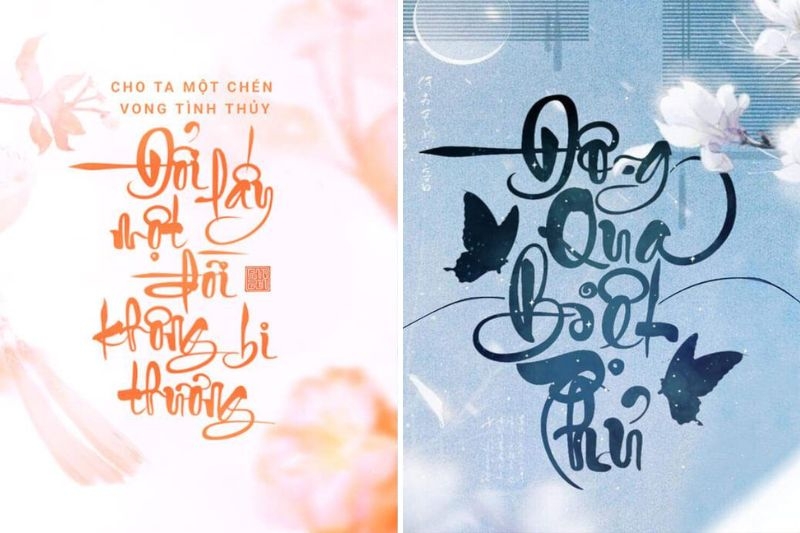
Top 10 font bảng chữ cái thư pháp đẹp, ấn tượng nhất
Dưới đây là top 10 font bảng chữ cái thư pháp đẹp và độc đáo nhất mà bạn có thể sử dụng trong các thiết kế của mình. Mỗi font chữ đều mang một phong cách riêng và phù hợp với nhiều loại ấn phẩm khác nhau. Hãy cùng FPT Shop khám phá và lựa chọn cho mình một kiểu chữ phù hợp nhé!
Font VN Lovelista
VN Lovelista được biết đến với các đường nét thư pháp mềm mại, uyển chuyển nhưng vẫn giữ được sự tinh tế và chắc chắn. Đặc biệt là sự kết hợp hoàn hảo giữa nét thanh và nét đậm không chỉ mang lại chiều sâu mà còn tôn lên tính nghệ thuật cho văn bản. Không khó hiểu khi Lovelista được giới sáng tạo ưu ái khi ứng dụng vào những thiết kế mang đậm bản sắc văn hóa Việt.
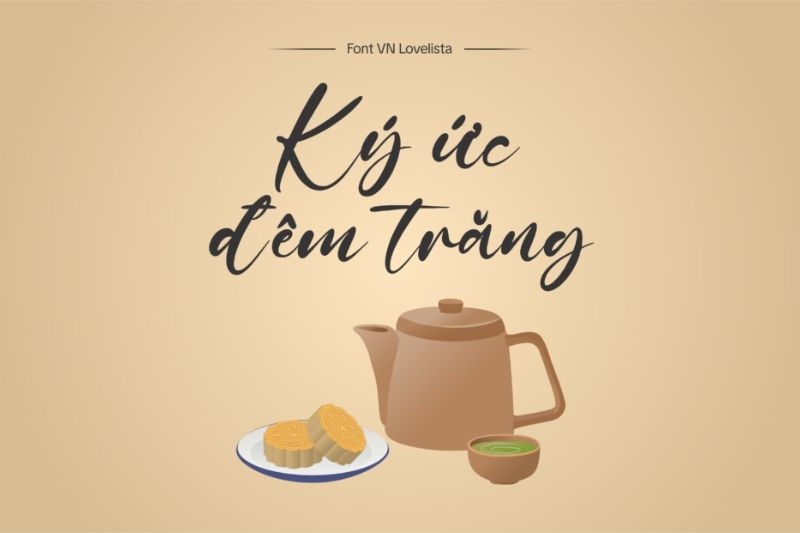
Font VN Opulent Brush
Font Opulent Brush là sự kết hợp táo bạo giữa nét mạnh mẽ, dứt khoát và phong thái phóng khoáng, tự do. Vì mô phỏng cách viết thư pháp của các ông đồ xưa, kiểu chữ này mang đến cảm giác cổ điển nhưng vẫn toát lên vẻ uy nghi, thần thái. Chính vì vậy, Opulent Brush thường được dùng cho các thiết kế mang tính nghi lễ, trang trọng như câu đối Tết hay ấn phẩm văn hóa dân gian.
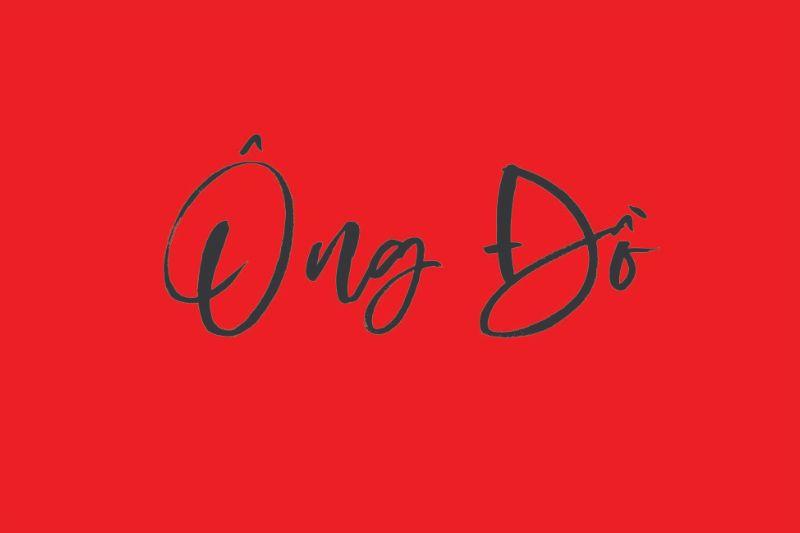
Font chữ Bendigo
Font bảng chữ cái thư pháp Bendigo nổi bật với sự tỉ mỉ và trau chuốt trong từng đường nét, đặc biệt là kiểu chữ hoa. Với vẻ đẹp hài hòa, Bendigo là lựa chọn hoàn hảo cho việc thiết kế tên thương hiệu, logo hoặc các ấn phẩm đòi hỏi tính trang trọng cao như giấy khen, thiệp mời, chứng chỉ,...
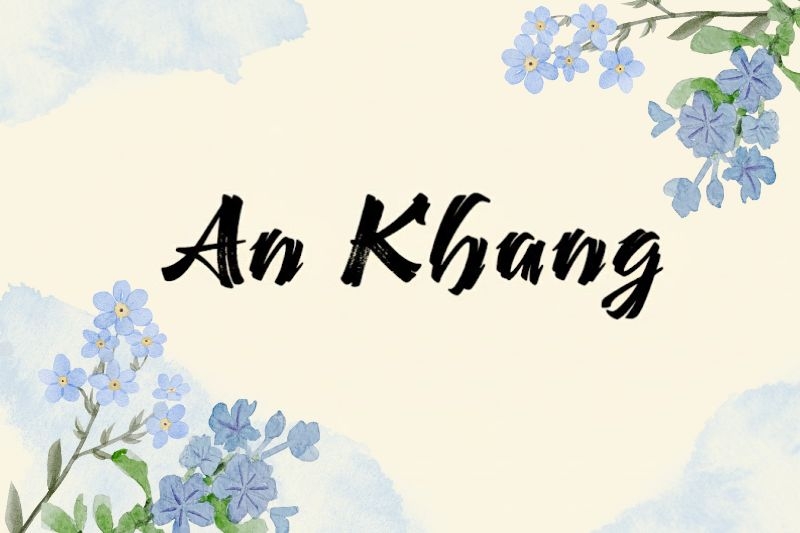
Font LNTH Watermark
Font LNTH Watermark được nhiều người yêu thích bởi những đường nét thanh mảnh, uốn lượn nhưng vô cùng thanh lịch. Kiểu chữ này gợi lên cảm giác nhẹ nhàng, yên bình như dòng nước chảy, cực kỳ lý tưởng cho các thiết kế thiên hướng tâm linh và thiền định. Vì lẽ đó mà bạn dễ dàng bắt gặp font chữ này trong các quyển Phật giáo, bảng hiệu cửa hàng phong thủy hay bìa kinh kệ.
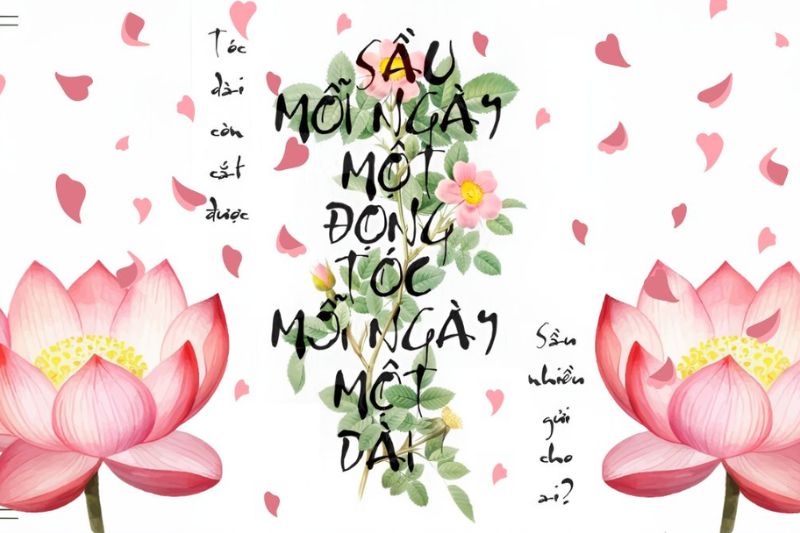
Font LNTH Dieter Steffmann
Font LNTH Dieter Steffmann là sự hòa quyện giữa nét thanh thoát, uyển chuyển và phong cách tươi mới nhưng vẫn giữ được vẻ trang trọng đặc trưng của thư pháp. Với tính thẩm mỹ cao, kiểu chữ này thường được dùng trong các thiết kế mang tính cảm xúc như thiệp chúc mừng, tri ân và ấn phẩm cho sự kiện lễ hội.
Bên cạnh đó, LNTH Dieter Steffmann cũng phù hợp để làm tài liệu giảng dạy, bìa sách hay quà tặng thủ công mang dấu ấn cá nhân.
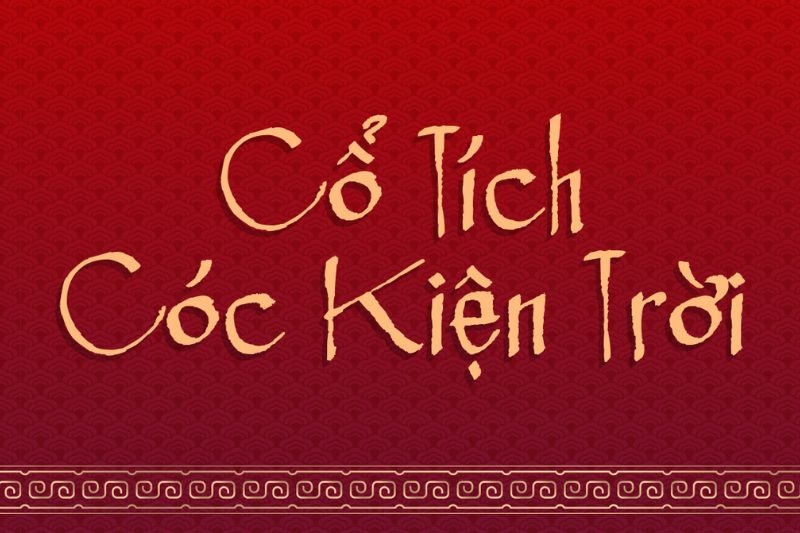
Font chữ Thành Công
Font bảng chữ cái thư pháp Thành Công gây ấn tượng bởi sự phá cách độc đáo nhưng vẫn giữ được nét văn hóa truyền thống. Những nét chữ dày, sắc sảo của font mang lại cho thiết kế cảm giác chắc chắn, mạnh mẽ và đầy cá tính. Ngày nay, font Thành Công thường được ứng dụng trong các ấn phẩm mang đậm không khí xuân như thiệp chúc Tết, bao lì xì hay quà handmade.
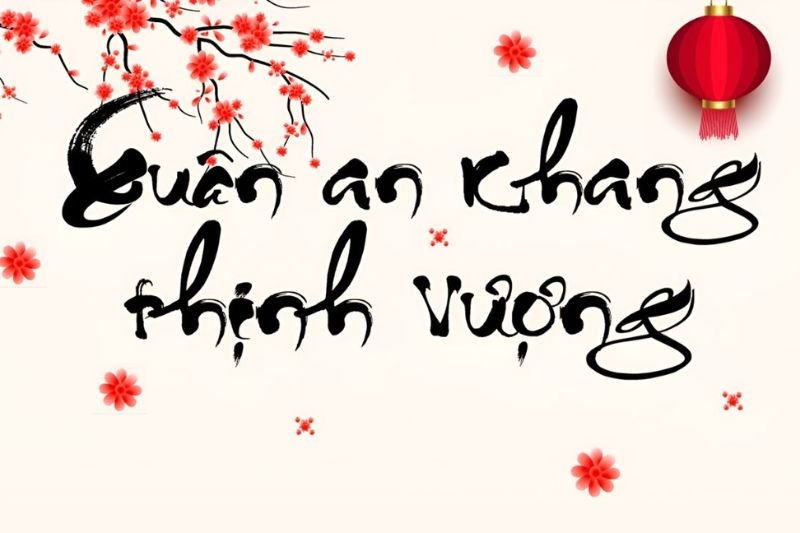
Font SVN Hottroof Semhesta
Font SVN Hottroof Semhesta sở hữu những đường nét mềm mại, uyển chuyển nhưng vô cùng tinh tế. Đặc biệt là kiểu chữ này còn mang đến một luồng năng lượng thanh tịnh và thiền định cho người xem. Có lẽ vì vậy mà Hottroof Semhesta được ưu tiên sử dụng cho các tác phẩm mang tính tĩnh tâm như kinh Phật, tranh thư pháp và các tài liệu hướng dẫn thiền.
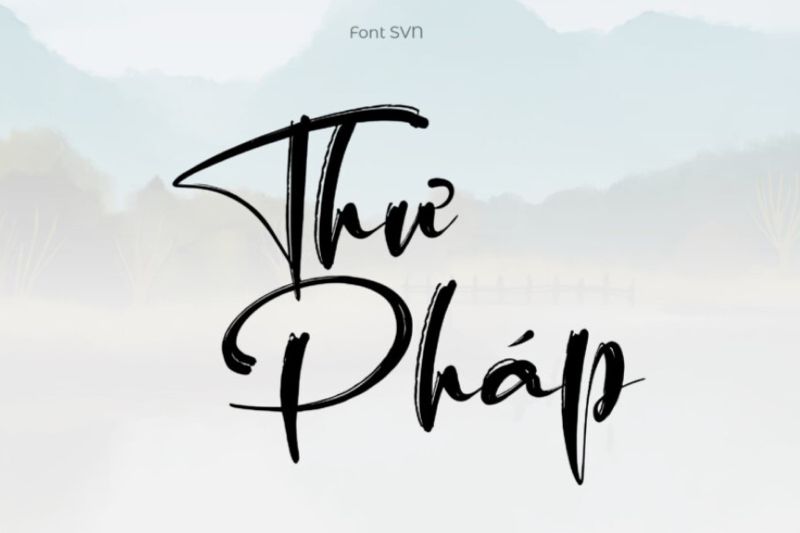
Font chữ Công Thuỷ
Font Công Thuỷ tái hiện trọn vẹn phong cách viết chữ của người xưa, nổi bật với những đường nét dày dặn, mạnh mẽ và các nét gạch đậm dứt khoát. Với nét đẹp văn hóa cổ điển, font bảng chữ cái thư pháp này phù hợp để thiết kế câu đối, thư pháp số hoặc các sản phẩm mang đậm dấu ấn truyền thống.
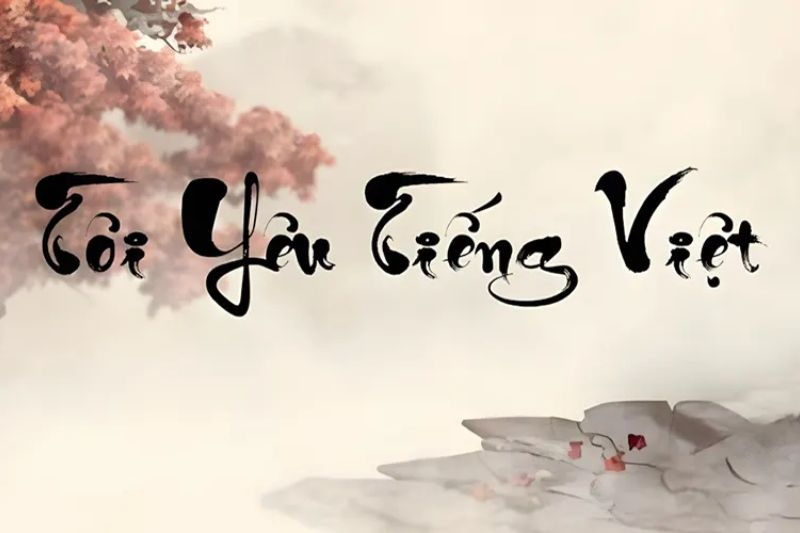
Font thư pháp Tiểu Tự
Font Tiểu Tự được tạo nên từ sự giao thoa giữa nét bút mềm mại và các điểm nhấn nhá đậm nhạt tinh tế. Từng đường nét đều được uốn lượn tinh xảo, thể hiện sự uyển chuyển, thanh thoát nhưng không hề thiếu đi sự dứt khoát. Do đó, font này rất phù hợp cho thiết kế mang tính nghệ thuật cao như poster, bìa sách, thiệp mời và các vật phẩm trang trí cá nhân hóa.
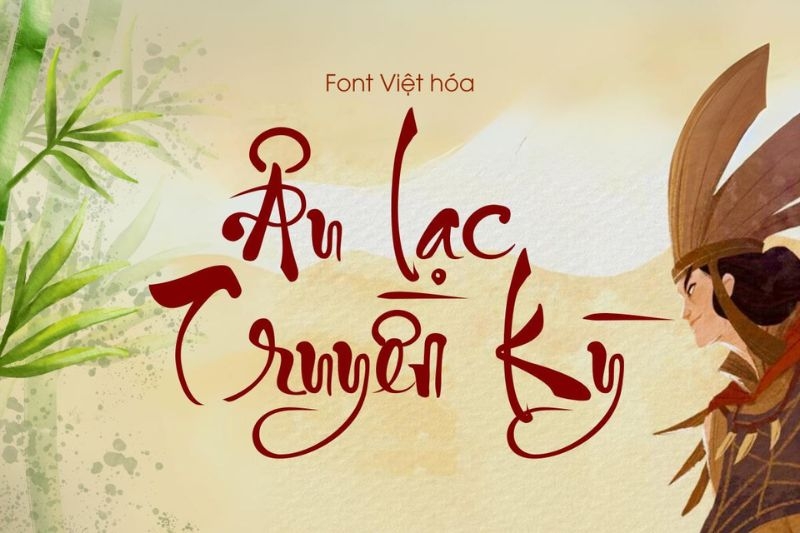
Font MTD Geza Script
Font MTD Geza Script là sự giao thoa hoàn hảo giữa nghệ thuật viết tay truyền thống và vẻ đẹp hiện đại. Với đường nét rõ ràng và dễ đọc, kiểu chữ này nhanh chóng trở thành lựa chọn hàng đầu cho các sản phẩm đòi hỏi sự trang trọng và chuyên nghiệp.